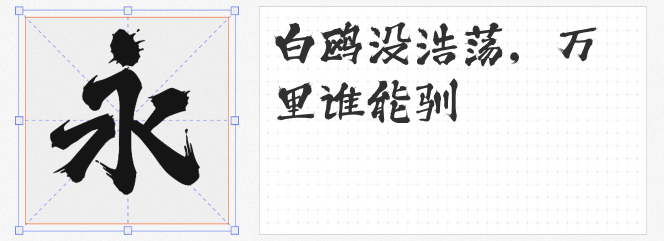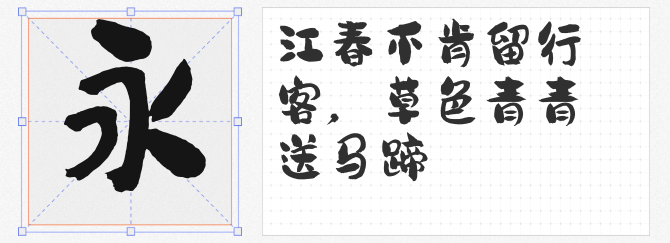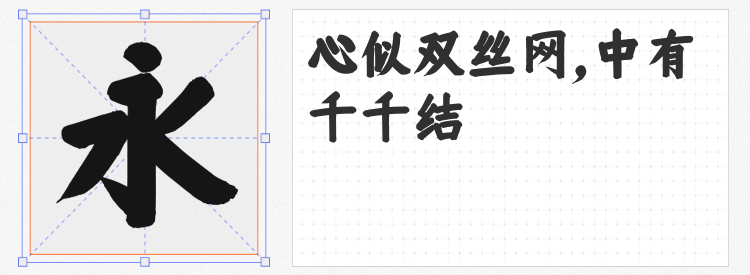
在国风设计盛行的当下,如何用字体传递江湖侠气与东方美学?这四款免费商用字体以独特笔触诠释水墨意境,助您轻松打造充满武侠风骨的视觉作品。
1. 龚帆免费体
这款字体以毛笔手写为魂,笔触间流淌着自然洒脱的韵律。圆润的笔画如侠客挥毫时的行云流水,转折处柔和无棱,仿佛能看见墨汁在宣纸上自然晕染的痕迹。无论是招牌题字还是短句文案,都能传递出"相逢一笑泯恩仇"的江湖温情,尤其适合茶馆、文创品牌等场景的视觉呈现。
2. 千图马克手写体
当书法遇上现代设计美学,便诞生了这款兼具传统气韵与当代阅读体验的字体。舒展的笔画布局如侠客仗剑天涯时的从容气度,字间留白恰似山水画中的虚实相生。其通透的排版特性使其既能驾驭酒馆菜单的标题,也能完美适配活动海报的提示文字,让每个字符都成为传递快意的视觉符号。
3. 三极泼墨体
这款字体将"泼墨成画"的意境发挥到极致,飞白的笔触如刀光剑影划破长空,浓淡相间的墨色变化暗藏内力涌动。不规则的笔画边缘仿佛诉说着"我命由我不由天"的豪情,特别适合游戏界面、摇滚专辑封面等需要突破常规的设计场景,让视觉呈现自带武侠BGM。
4. 仓耳周珂正大榜书
作为专业字库出品的艺术字体,这款作品在传统榜书基础上进行现代化改良。匀称的笔画粗细与端正字形暗合"中正平和"的武学至理,既能展现镖局招牌的厚重感,又可诠释茶道品牌的雅致意境。、
从市井烟火到武林风云,这四款字体如同四把不同风格的江湖利刃,助您在设计中斩破平庸,书写独属东方的视觉传奇。